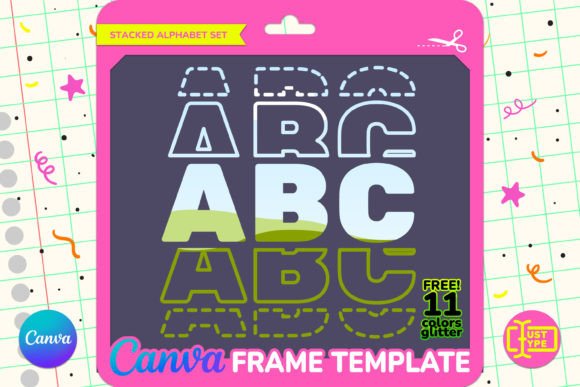
Draft Stacked Alphabet Canva Frame
Mencari elemen reka bentuk yang sesuai boleh menjadi mencabar, tetapi Draft Stacked Alphabet Canva Frame menawarkan koleksi luar biasa yang menaik taraf karya anda serta-merta.
Sama ada anda mencipta produk POD (Print on Demand), jemputan perkahwinan atau grafik media sosial, Draft Stacked Alphabet Canva Frame amat bersesuaian.